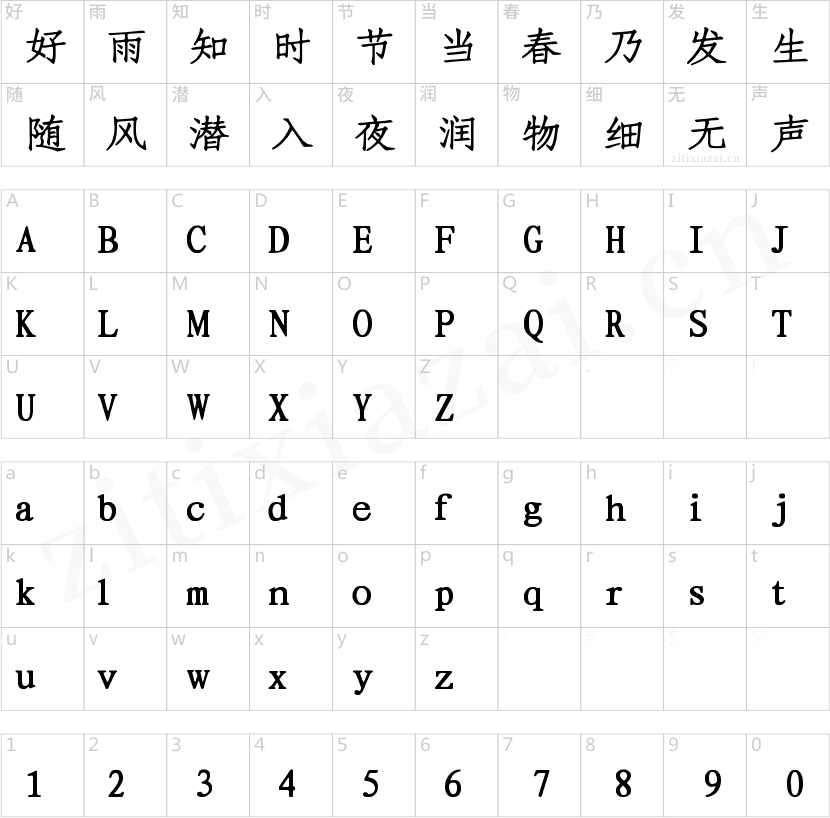
字魂正文宋楷
字魂正文宋楷,这款字体结构工整、笔画清晰,兼顾美观与易读性,适用于标题、正文、海报、包装、LOGO 等多种场景。字形优雅稳定,风格百搭耐看,适配日常排版与创意设计,让文字呈现更舒适、更具质感。字魂正文宋楷一笔一画,皆是细节,以均衡的比例、流畅的线条打造舒适视觉体验,字形端正大气,风格简约现代。无论是商业设计、品牌宣传还是日常排版,都能轻松驾驭,让文字更有格调与力量。字魂正文宋楷字体下载。